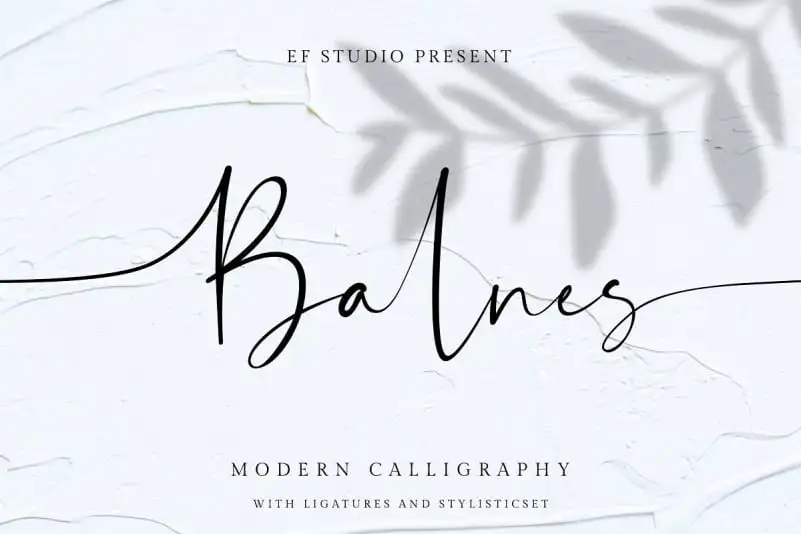
Esta fonte script é perfeita para aqueles que buscam uma mistura de elegância com naturalidade na sua identidade visual. Intitulada Balnes Script Font, foi criada pelo designer Ef Studio e apresenta um estilo moderno e sofisticado, combinando afeição ao texto manuscrito com elementos tipográficos detalhados. Ela é perfeitamente adequada para aplicar em uma variedade de ambientes: desde embalagens, selos e cartões promocionais até criações digitais como marcas de água e capas de filme de cinema. Com letras maiúsculas e minúsculas completas, estilos únicos e símbolos multilinguísticos que permitem uma grande variedade de combinações, a Balnes Script é perfeita para qualquer tipo de design gráfico. Seja você um designer digital buscando adicionar aquele toque especial às suas criações ou um profissional de marketing à procura de algo único para seus materiais de comunicação, essa fonte oferece uma opção única e impecável. Balnes Script é a escolha perfeita para aquela identidade visual que quer soar pessoal e moderna ao mesmo tempo.